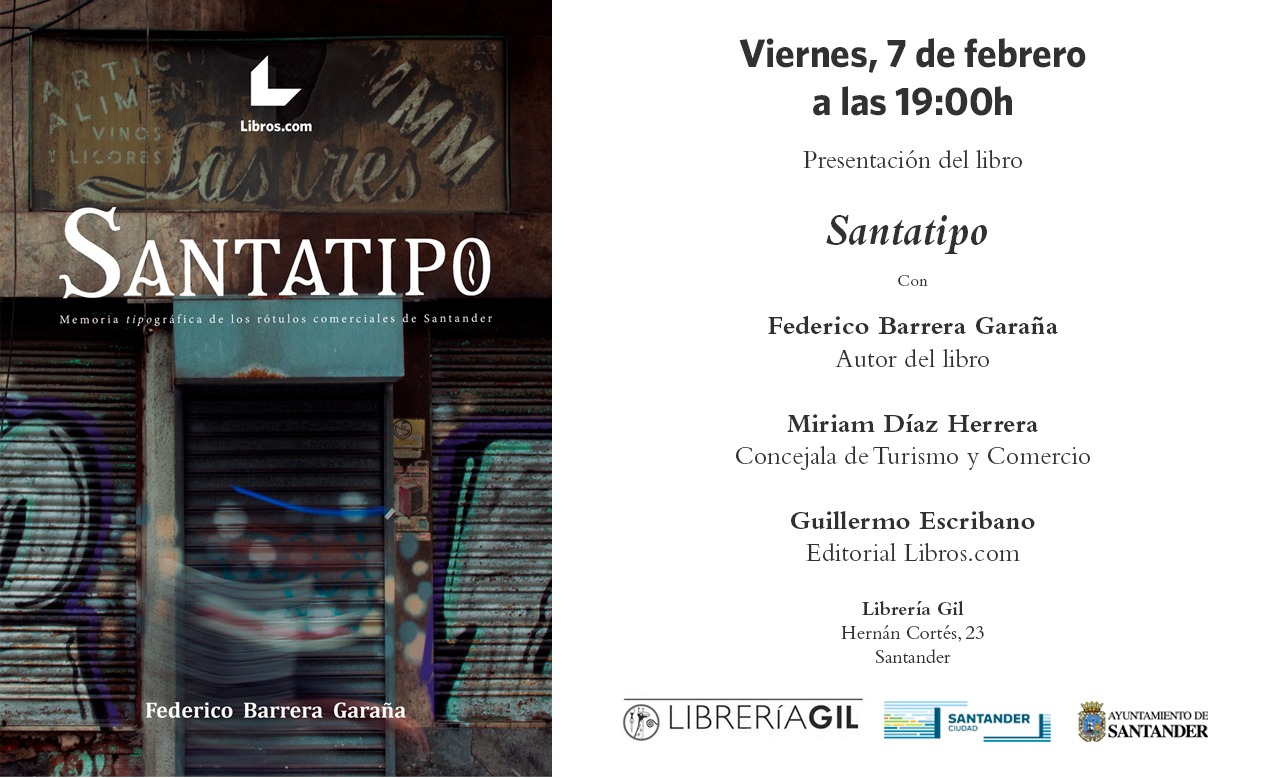
Presentación y venta del libro de «Santatipo»
Desde hoy 7 febrero ya se puede adquirir el libro «Santatipo: Memoria tipográfica de los rótulos comerciales de Santander» un trabajo, que es un breve resumen de estos 5 años de proyecto. El libro nació con la intención de dejar una preservación y documentación bibliográfica para el futuro de la ciudad. Ha sido financiado a través de una campaña de crowdfounding a través de la editorial Libros.com, con el apoyo de más de 100 Mecenas y el Ayuntamiento de Santander.
La obra cuenta con más de 100 rótulos de la ciudad, combinados con fotos actuales, de archivo y reconstrucciones, acompañados en su gran mayoría por parte de su pequeña historia. Una historia que trasciende al rótulo, porque habla de gente de barrio, de comercios desaparecidos, de los rótulos como testigos identitarios de las calles de las ciudades. Unas ciudad que hoy día se están unificando visualmente. Es por ello que ya varios proyectos se han unido para trabajar en salvaguadarlos para el futuro como un #PatrimonioGráfico